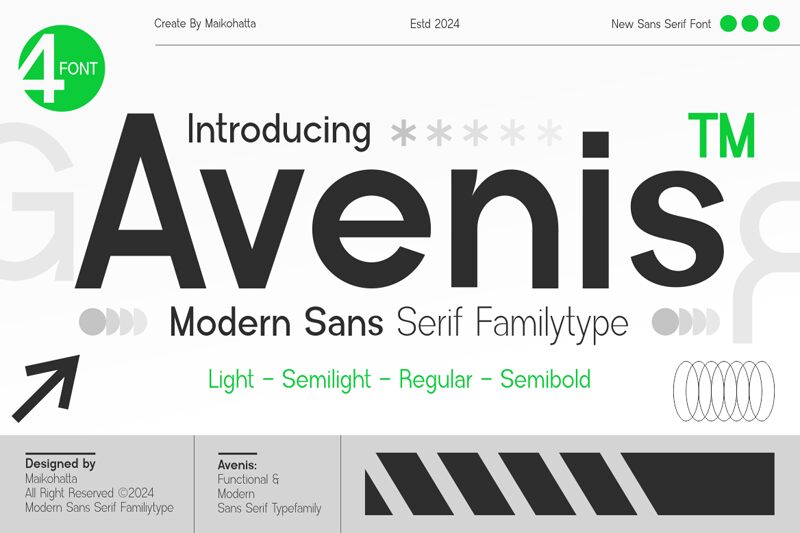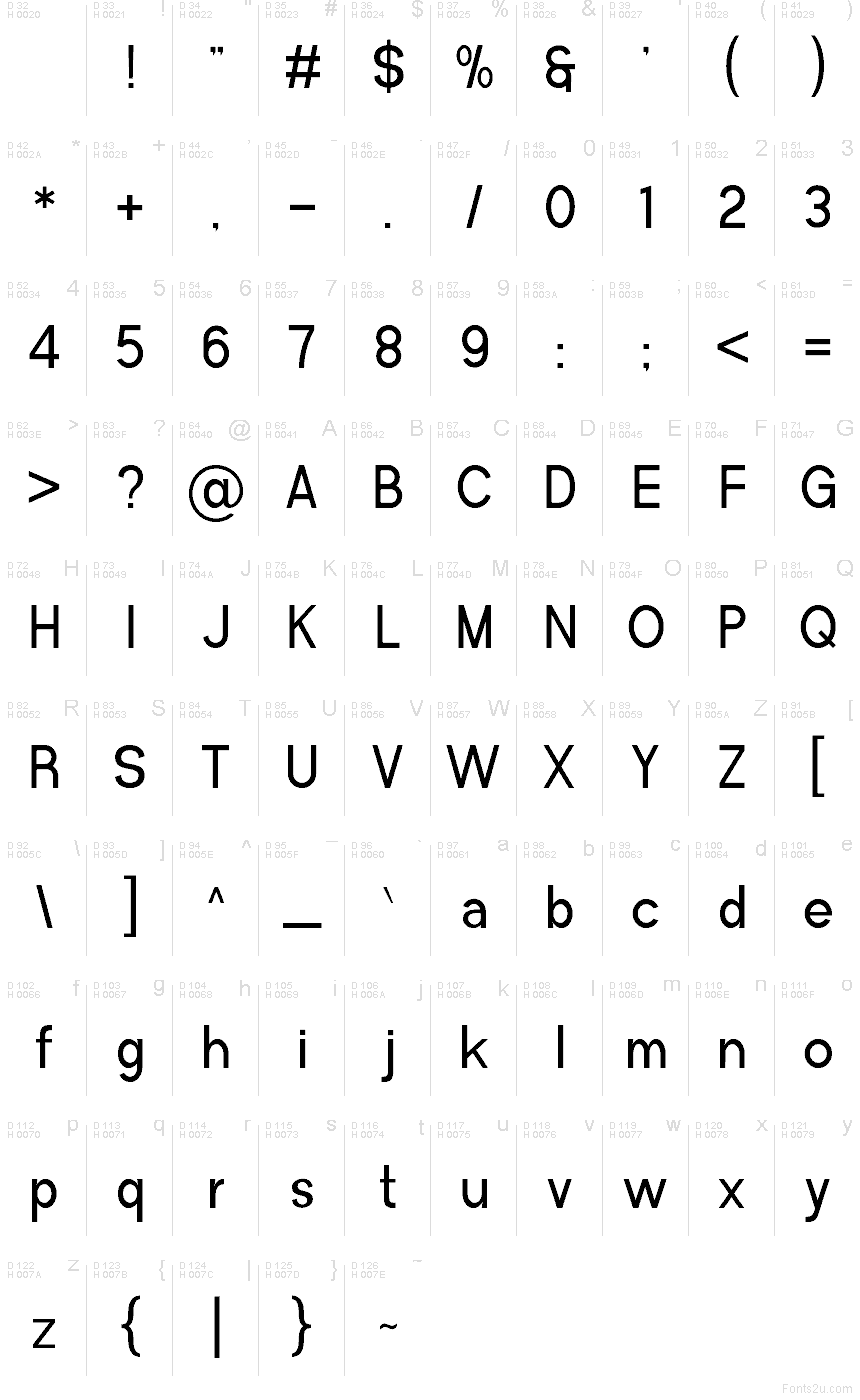
Avenis di Maikohatta è un font sans serif gratuito dalla voce nitida e diretta, con un ritmo sorprendentemente amichevole. I suoi tratti puliti e la spaziatura aperta rendono il marchio visivamente leggero, mentre le forti verticali gli conferiscono una struttura solida, garantendo un'ottima leggibilità a colpo d'occhio. È quel tipo di carattere che rimane calmo e leggibile senza mai risultare banale.
Con Avenis, avrai una chiarezza affidabile per etichette UI, titoli di app, loghi di brand, poster minimalisti, sottotitoli editoriali, pitch deck, annunci social e grafica di segnaletica. Mantienilo leggermente arioso con un tocco di tracking extra per un feeling moderno, oppure stringilo per una navigazione più compatta. Abbina questo font gratuito a un carattere serif caldo per il testo principale, aggiungendo contrasto senza perdere il suo tono pulito.